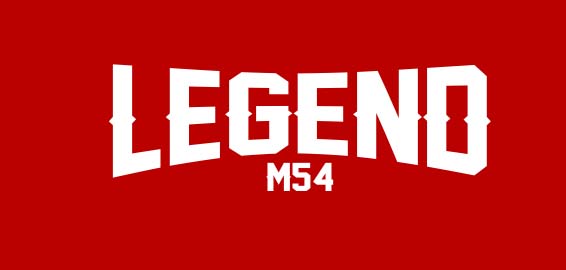
Continua la nostra raccolta di font inspiration, in quello odierno vi presento qualcosa di davvero creativo e “fuori dalle righe”. Si chiama Karabine e ovviamente è completamente gratuito.
Come vedete il font risulta molto fresco e creativo ed è adatto a coloro che cercano qualcosa di “diverso”dal solito.